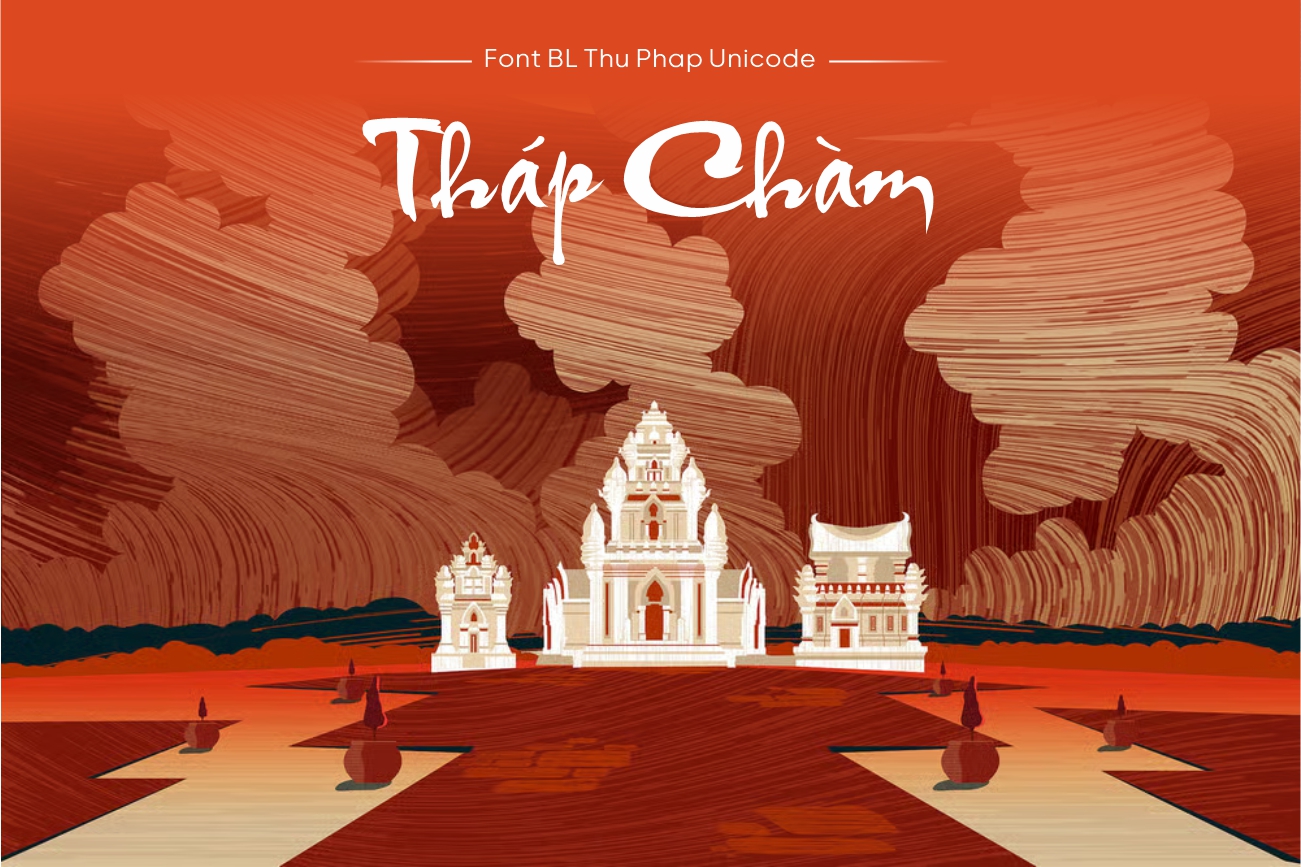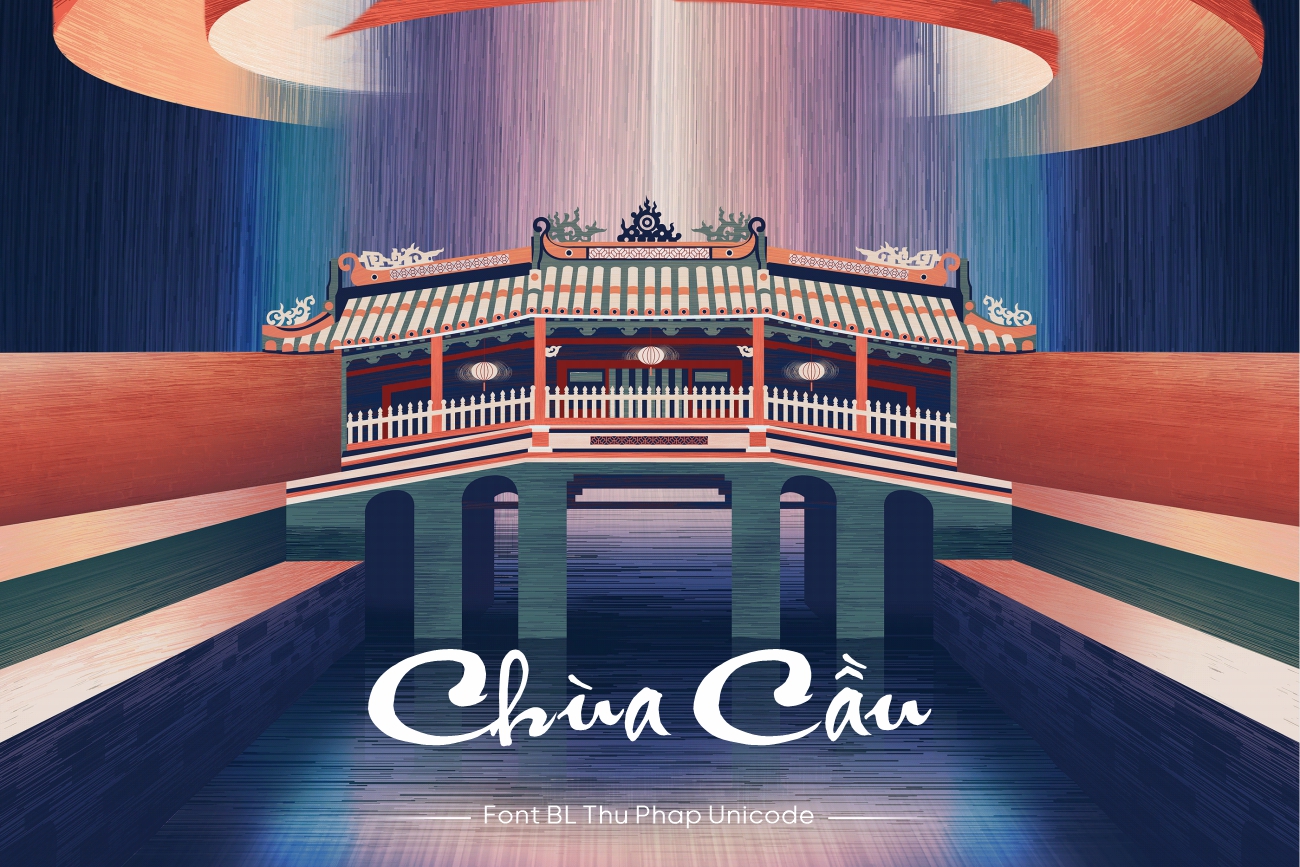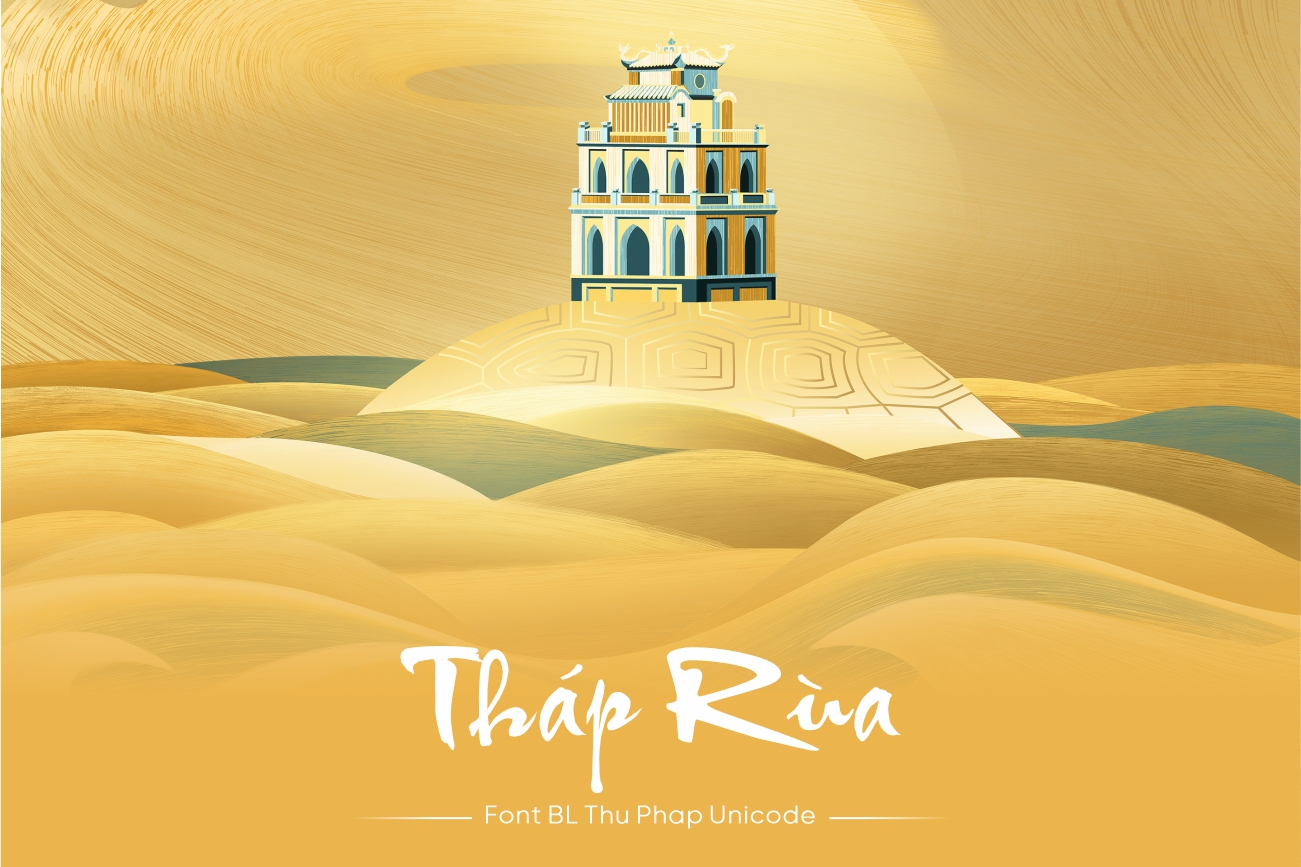
Font chữ BL Thư Pháp – Vẻ đẹp uyển chuyển của thư pháp Việt
Nếu bạn đang tìm kiếm một font chữ mang hơi thở truyền thống nhưng vẫn đảm bảo tính ứng dụng cao trong thiết kế hiện đại, BL Thư Pháp Uni chắc chắn sẽ là lựa chọn phù hợp. Font chữ này mô phỏng lối viết tay mềm mại, uyển chuyển như những nét bút lông trong nghệ thuật thư pháp Á Đông, mang lại cảm giác vừa cổ điển, vừa lãng mạn.
Điểm nổi bật của BL Thư Pháp Uni nằm ở khả năng tạo nên không gian nghệ thuật độc đáo cho thiết kế. Những đường nét mềm mại, bay bổng giúp chữ viết trở nên sinh động, giàu cảm xúc. Chính vì vậy, font thường được dùng trong poster, câu đối hay các sản phẩm gắn liền với văn hóa truyền thống Việt Nam.
Font chữ này do Team BL phát triển, dựa trên nền tảng VNI Thufap 2 và được chỉnh sửa để tương thích với bảng mã Unicode. Ngoài ra, font còn được tối ưu về kerning (khoảng cách chữ) và khắc phục những lỗi nét thường gặp trong quá trình gia công CNC hoặc cắt decal – điều mà nhiều nhà thiết kế quảng cáo rất quan tâm. Nhờ vậy, khi áp dụng vào thực tế, BL Thư Pháp Unicode vừa giữ được vẻ đẹp nghệ thuật, vừa đảm bảo tính chính xác và độ sắc nét.
Với sự kết hợp giữa nét truyền thống và tính tiện dụng, BL Thư Pháp Uni không chỉ là một font chữ đơn thuần, mà còn là công cụ giúp các nhà thiết kế truyền tải cảm xúc và tinh thần của thư pháp Việt vào từng sản phẩm. Nếu bạn muốn tạo nên dấu ấn sang trọng, đậm chất Á Đông cho dự án của mình, đừng bỏ qua font chữ độc đáo này.